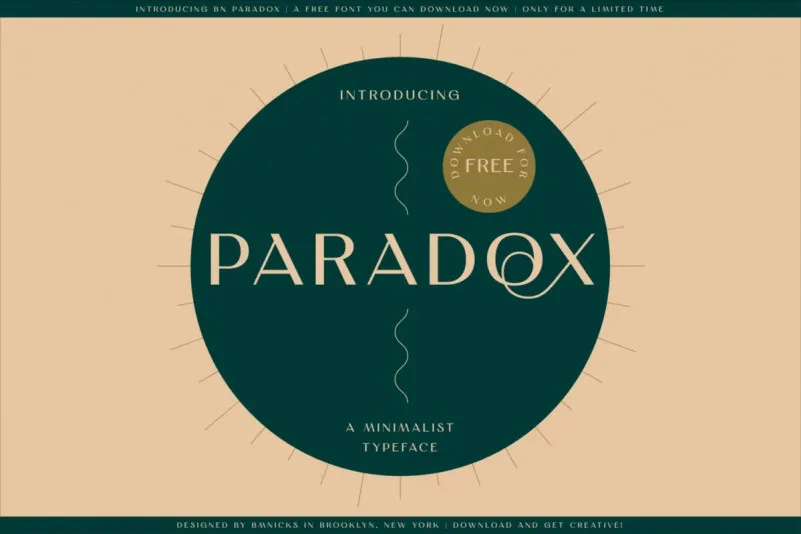
BN Paradox Free Font – Download Grátis
A fonte ‘BN Paradox Free Font’ é uma escolha perfeita para aqueles que desejam dar a sua marca ou projeto um toque moderno e arrojado. Inspirada no tipo geométrico, esta fonte Geometric Sans Typeface foi criada pelo designer Brandon Nickerson Studio e apresenta aspectos dinâmicos e joviais, como resultado de seu carácter forte e poderoso. Caracterizada por linhas robustas e finas com texturas suaves, ‘BN Paradox Free Font’ combina perfeitamente com as necessidades de empresas digitais e criativas. Ideal para estabelecimentos que desejam um visual contemporâneo e atraente, esta fonte é particularmente adequada para o público jovem – aqueles nascidos na década de 1980 ou posterior – uma faixa etária dominante entre os empreendedores digitais. Com seu design agressivo e energético, ‘BN Paradox Free Font’ é uma escolha sólida tanto para aplicações comerciais quanto para projetos criativos. Perfeita para empresas que querem dar sua identidade visual um tom mais arrojado sem sair muito da linha tradicional de tipo geométrico. Não importa o seu propósito, ‘BN Paradox Free Font’ oferece a praticidade e qualidade necessárias para tornar qualquer projeto notável e imponente.